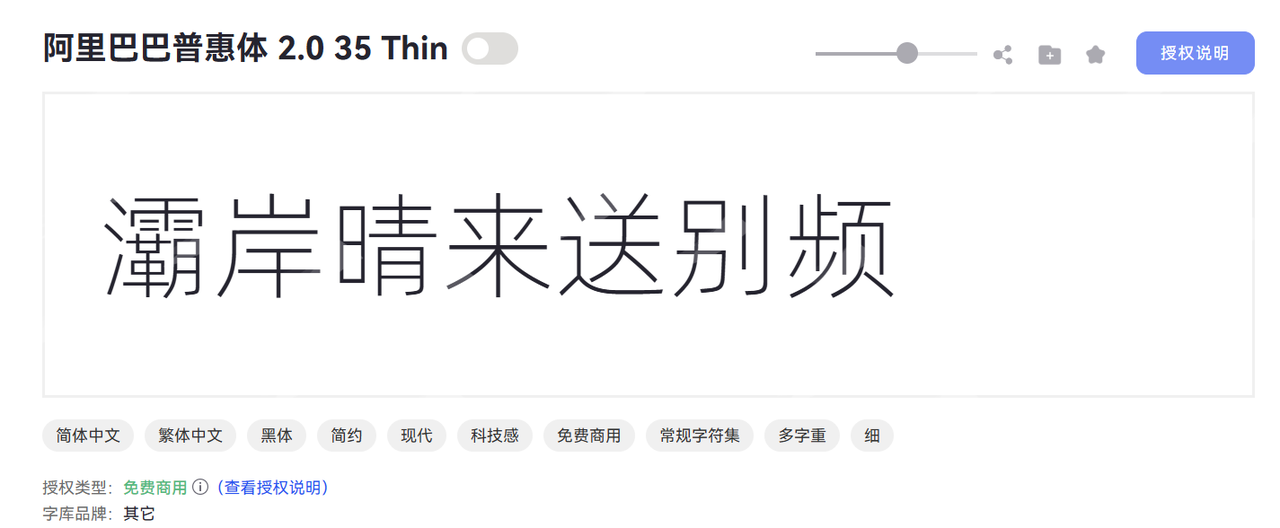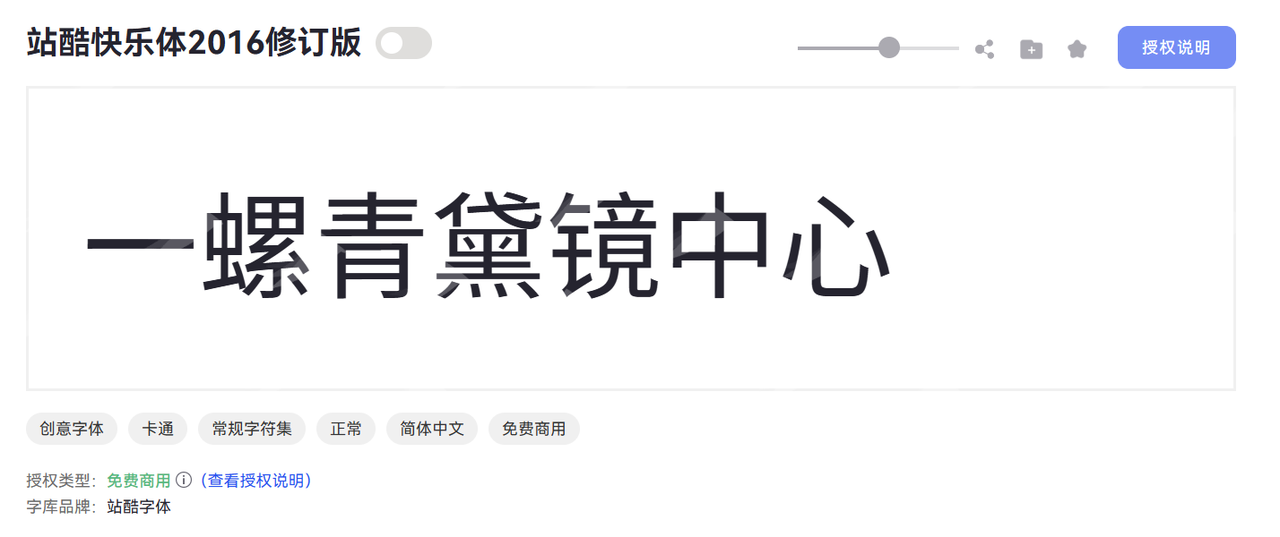
适合制作长图的字体推荐,三类长图场景字体应用案例
做新媒体运营,每周至少要出5-8张长图,公众号推文、小红书笔记、知乎专栏配图都需要。刚开始我也踩过很多坑,字体要么在长图里看不清,要么层次感不够,用户根本不愿意往下滑。后来我慢慢摸索出一套选字体的方法,今天分享给你。
为什么长图对字体要求特别高
长图和普通海报不一样。用户是在手机屏幕上从上往下滑动看的,一张长图可能有五六屏的内容。如果字体选得不对,会出现这几个问题:
第一是可读性差。很多艺术字在电脑上看着挺漂亮,放到手机上就糊成一团,特别是笔画复杂的字体,缩小后根本看不清。
第二是层次不分明。长图内容多,需要用不同字体区分标题、副标题、正文。如果全用一种字体,用户看着累,抓不住重点。
第三是风格不统一。我见过有人一张图里用五六种字体,看着特别乱。其实两到三种字体搭配好就够了。
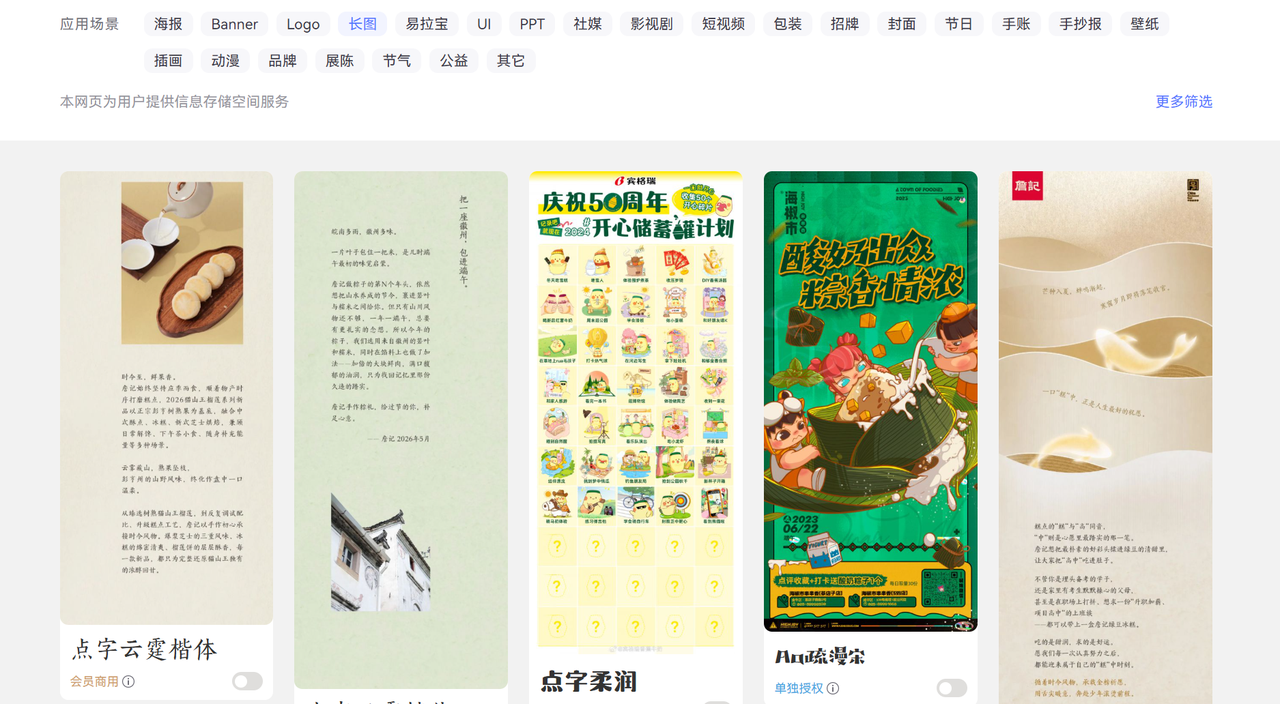
不同场景下我常用的字体
知识科普类长图
这类长图信息量大,用户是来学东西的,字体首要任务是看得清楚、看得舒服。
标题字体:阿里巴巴普惠体
这是我用得最多的标题字体。它是黑体系列,笔画粗壮有力,在手机屏幕上辨识度很高。关键是阿里开源的,可以免费商用,完全不用担心版权问题。我一般把字号设置在48-60pt,颜色用深色或者品牌色,一眼就能看出是标题。
正文字体:思源黑体
正文我基本都用思源黑体。它是Adobe和Google联合开发的开源字体,最大的优点是不同字重特别全,从ExtraLight到Heavy有七个字重。我做长图正文用Regular,小标题用Medium,层次感立刻就出来了。字号一般是28-32pt,行距设置1.5倍,读起来不费劲。
强调字体:阿里巴巴普惠体
有些数字或关键词需要突出,我会用普惠体的Medium字重,配合品牌色或者橙色。比如"提升300%"这种数据,单独拎出来用大字号,用户一眼就能看到。
这个组合我用在干货类、教程类长图上,效果一直不错。去年我做过一个《小红书涨粉指南》的长图,用的就是这套字体,阅读完成率达到62%,比平时高了一倍。
情感文案类长图
这类长图讲故事、讲感受,需要字体有点温度,不能太冷冰冰。
标题字体:站酷快乐体
站酷快乐体是手写风格,笔画圆润,看着亲切。我做情感类、生活类内容时经常用它做主标题。它的识别度很好,不会因为是手写体就看不清。而且站酷也是免费商用的,放心用。
正文字体:思源宋体 Regular
宋体比黑体多了一份文艺感。思源宋体的笔画细节处理得很好,小字号下也清晰。我做书单推荐、读书笔记这类长图时,正文就用思源宋体,配合米色或浅灰色背景,整体氛围立刻就有了。
点缀字体:濑户字体(用于金句)
濑户字体也是免费字体,风格偏可爱清新。我会在长图里挑一两句金句,用濑户字体放大,配合插画或者装饰元素。这种处理方式在小红书上特别受欢迎,用户看到金句会主动截图保存。
促销活动类长图
活动类长图要让人一眼看到优惠信息,字体要醒目、直接。
主标题字体:庞门正道标题体
庞门正道标题体笔画粗,视觉重量足,天生适合做促销标题。"限时五折""买一送一"这种文案用它,在一堆内容里特别跳。这款字体也是免费商用,很多电商设计师都在用。
价格字体:阿里巴巴普惠体
价格必须用最粗的字重,我一般用普惠体的Heavy,把字号放到80pt以上,颜色用红色或橙色。用户滑到这里,视线一定会停留。
说明文字:思源黑体
活动规则、使用说明这些内容,用常规字重的黑体就行,别抢了主角的风头。字号控制在24-28pt,颜色用灰色,保证看得清就够了。
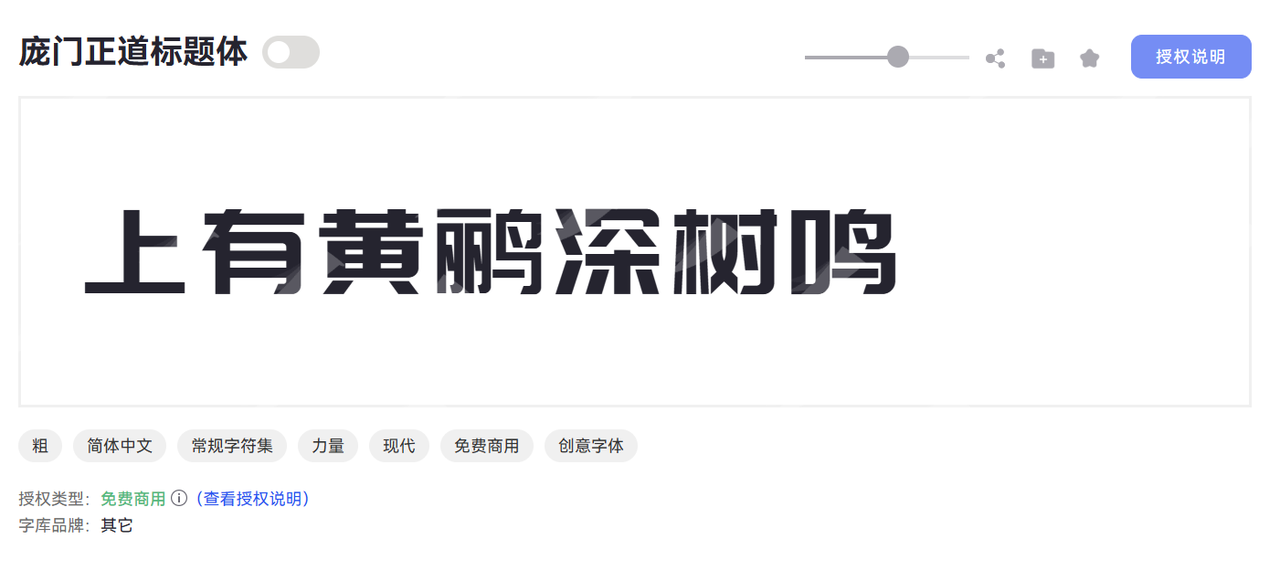
更多的长图字体案例
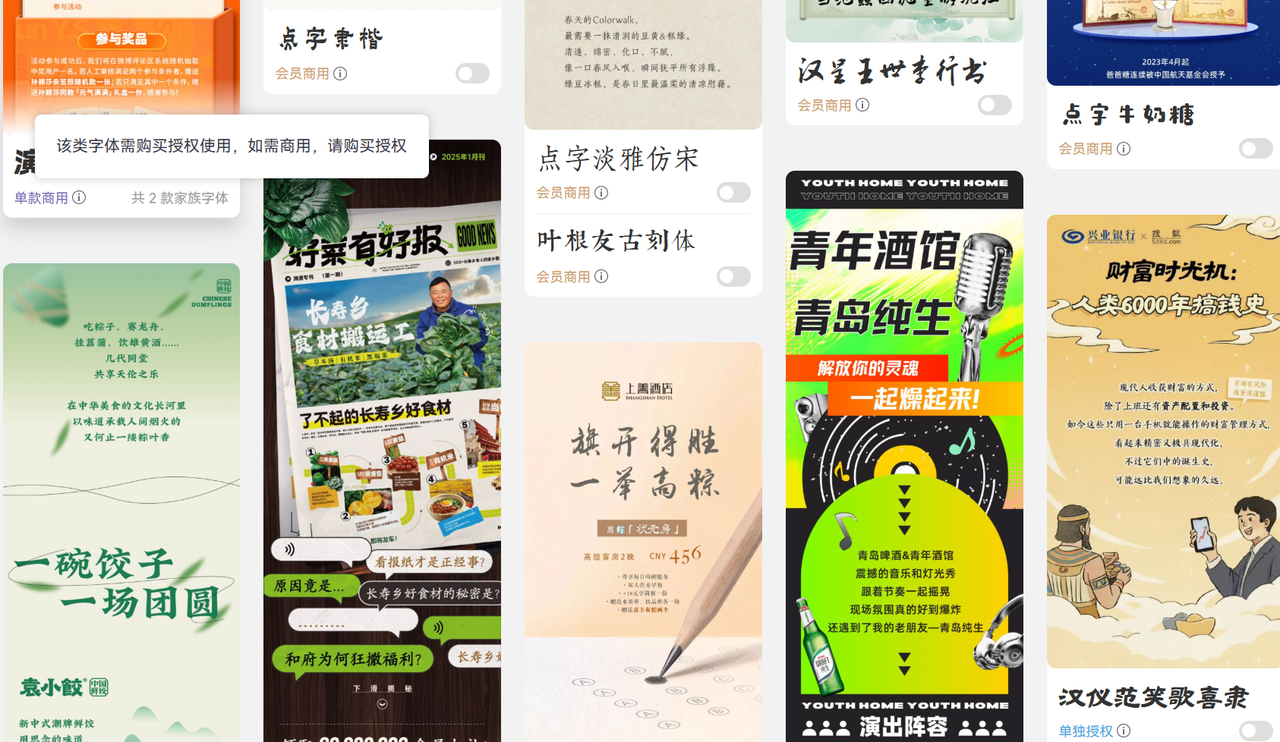
选字体这件事,没有标准答案,适合你的内容风格和用户群体才是最重要的。我分享的这些字体和方法,都是我这几年踩坑总结出来的,你可以直接拿去用。
刚开始做长图时别想太多,就用思源黑体+阿里巴巴普惠体这个组合,肯定不会出错。等你做了几十张长图,自然就知道什么场景该用什么字体了。